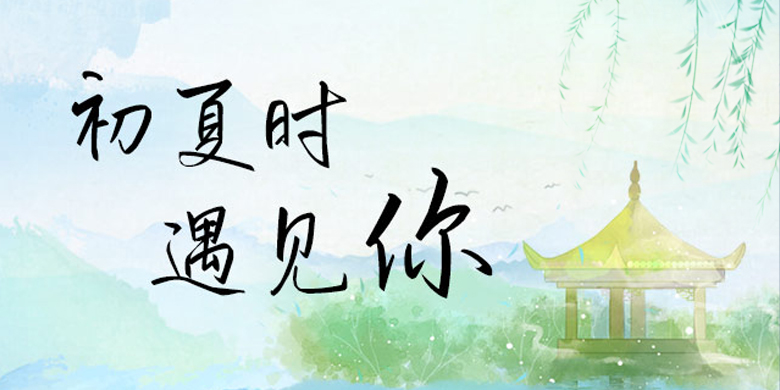
方正手迹-初夏时遇见你
字体品牌: 方正手迹 设计师:尚正中 字体分类:创意书写 字体属性:精品字 字符集:大陆简体(GB2312-80) 发布时间: 2020
初夏时遇见你这款字体用笔细腻,笔画舒展,提按顿挫极具古意,传统书法与现代气息兼备,端庄优雅韵味十足。适用于文化类宣传、文艺类的书刊、品牌广告和产品包装设计,综艺影视用字,以及社交网络的个性化用字。